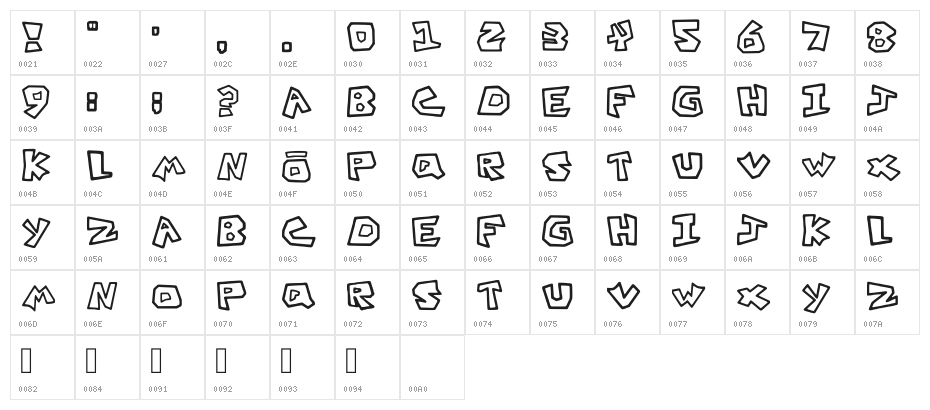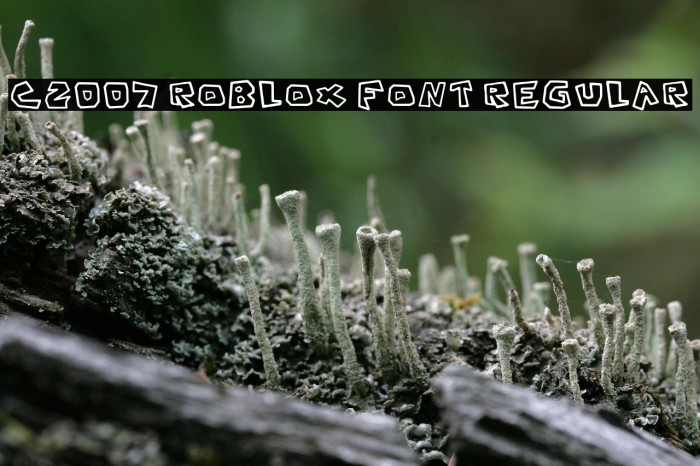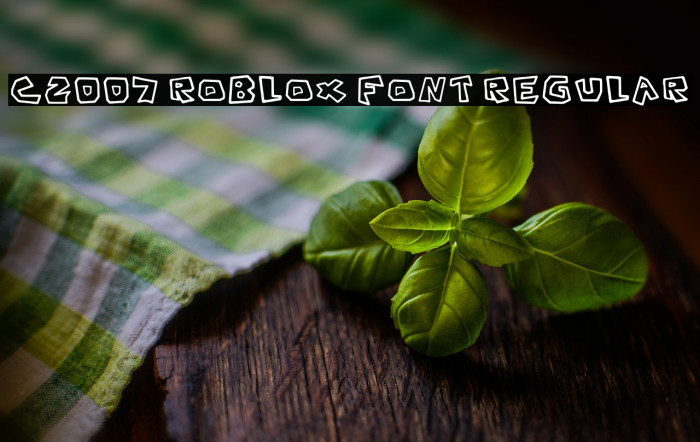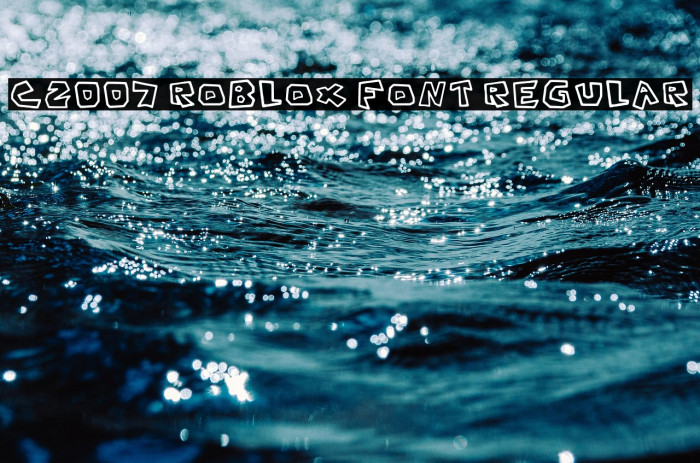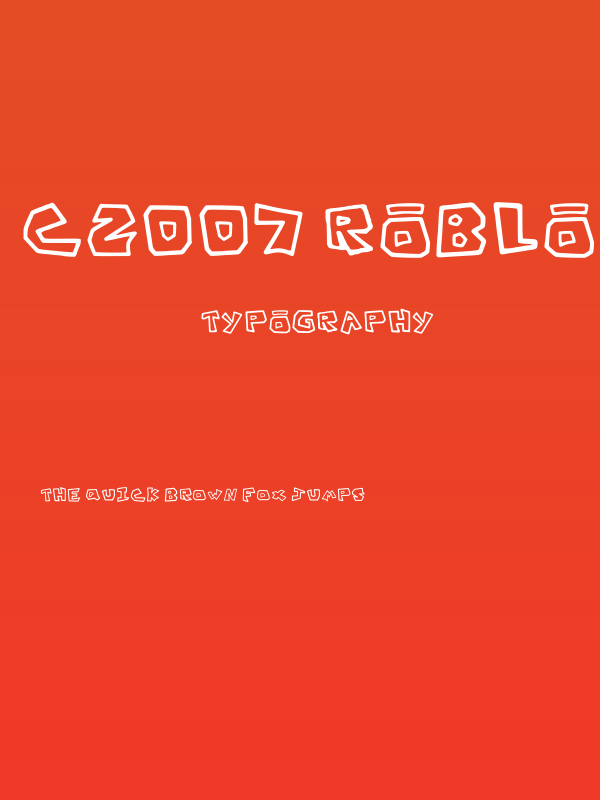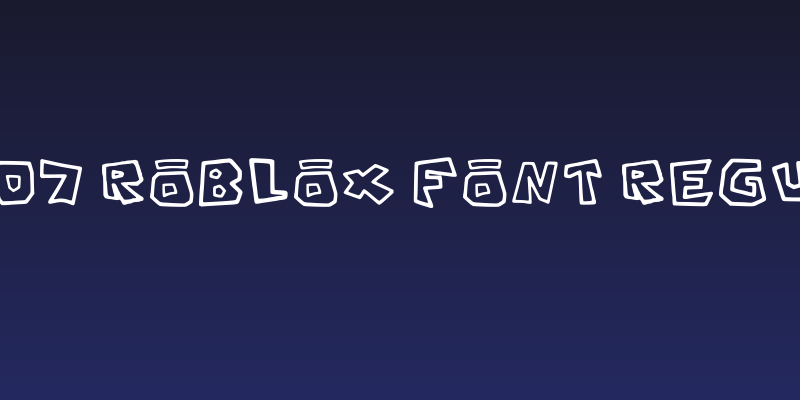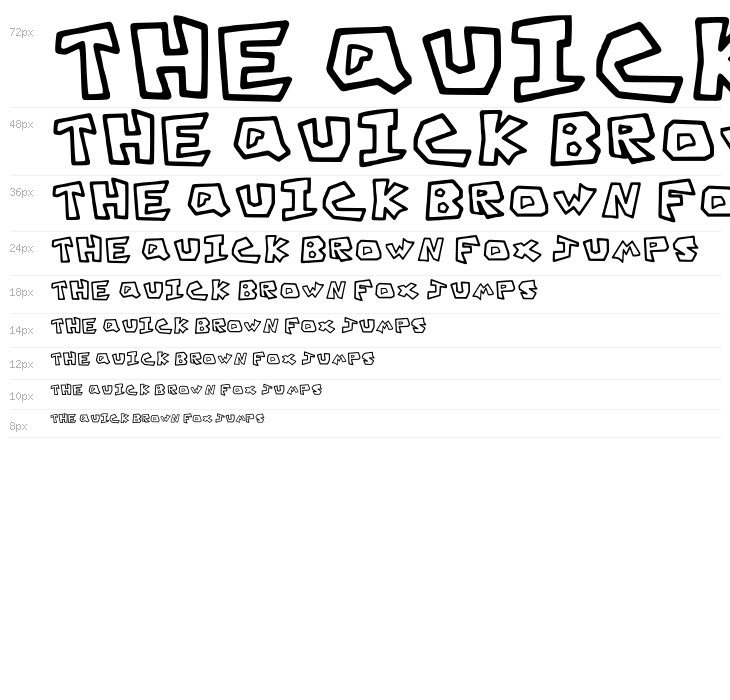
C2007 Roblox Font Regular Font
| Stile generale | Playful, Cartoonish |
| Progetti proposti | Ideal for children's books, comic strips, video game graphics, and playful branding. |